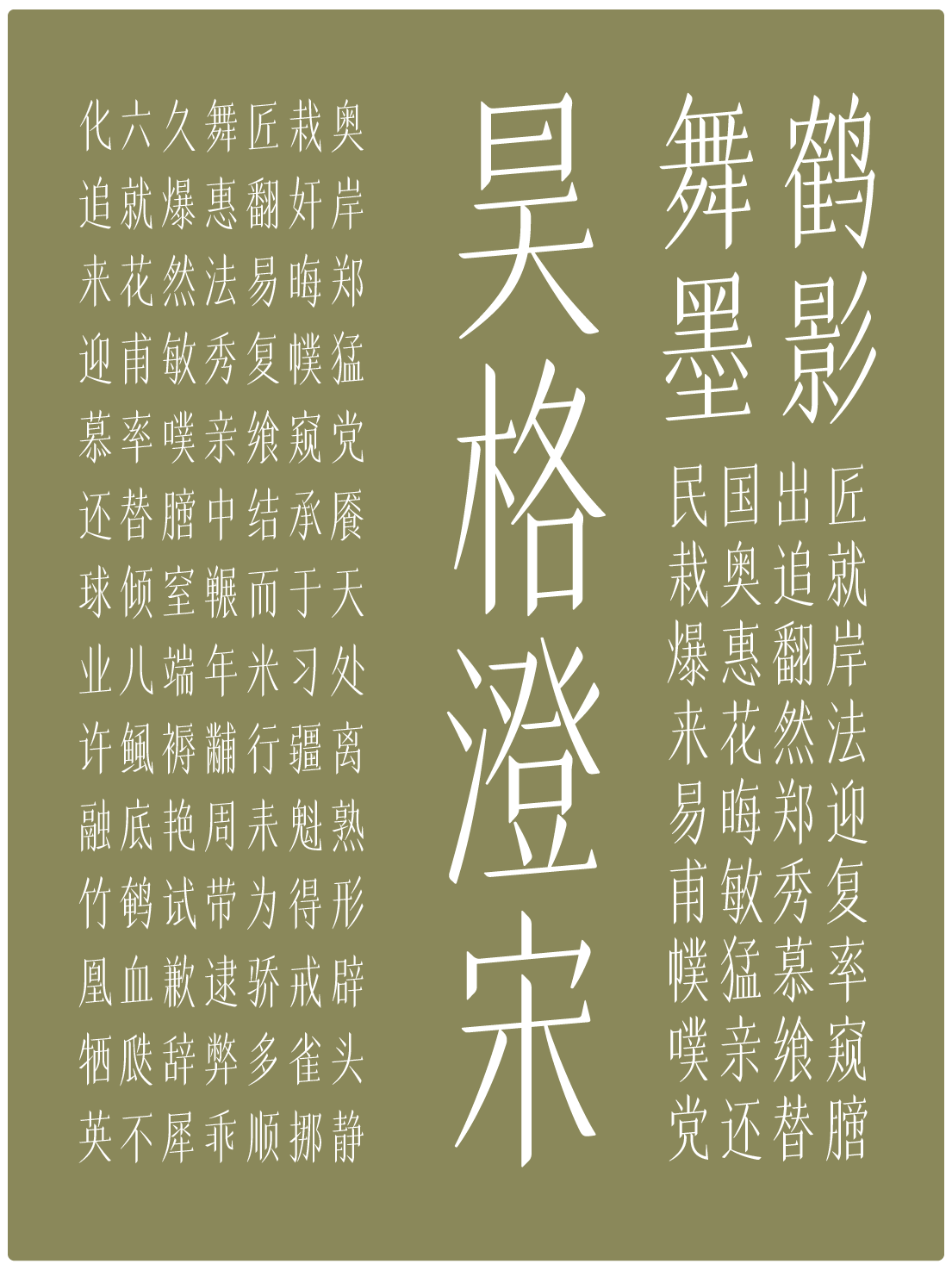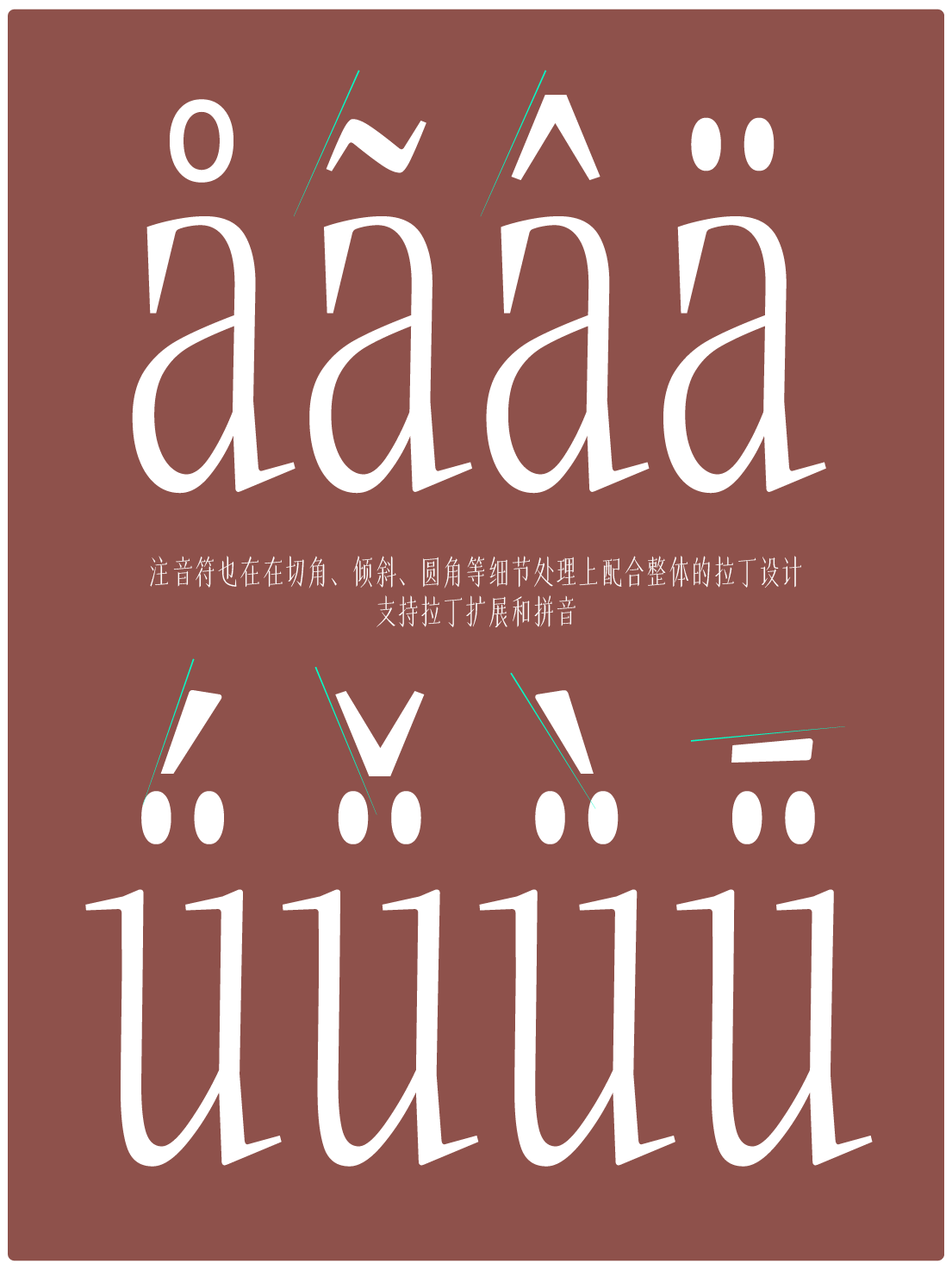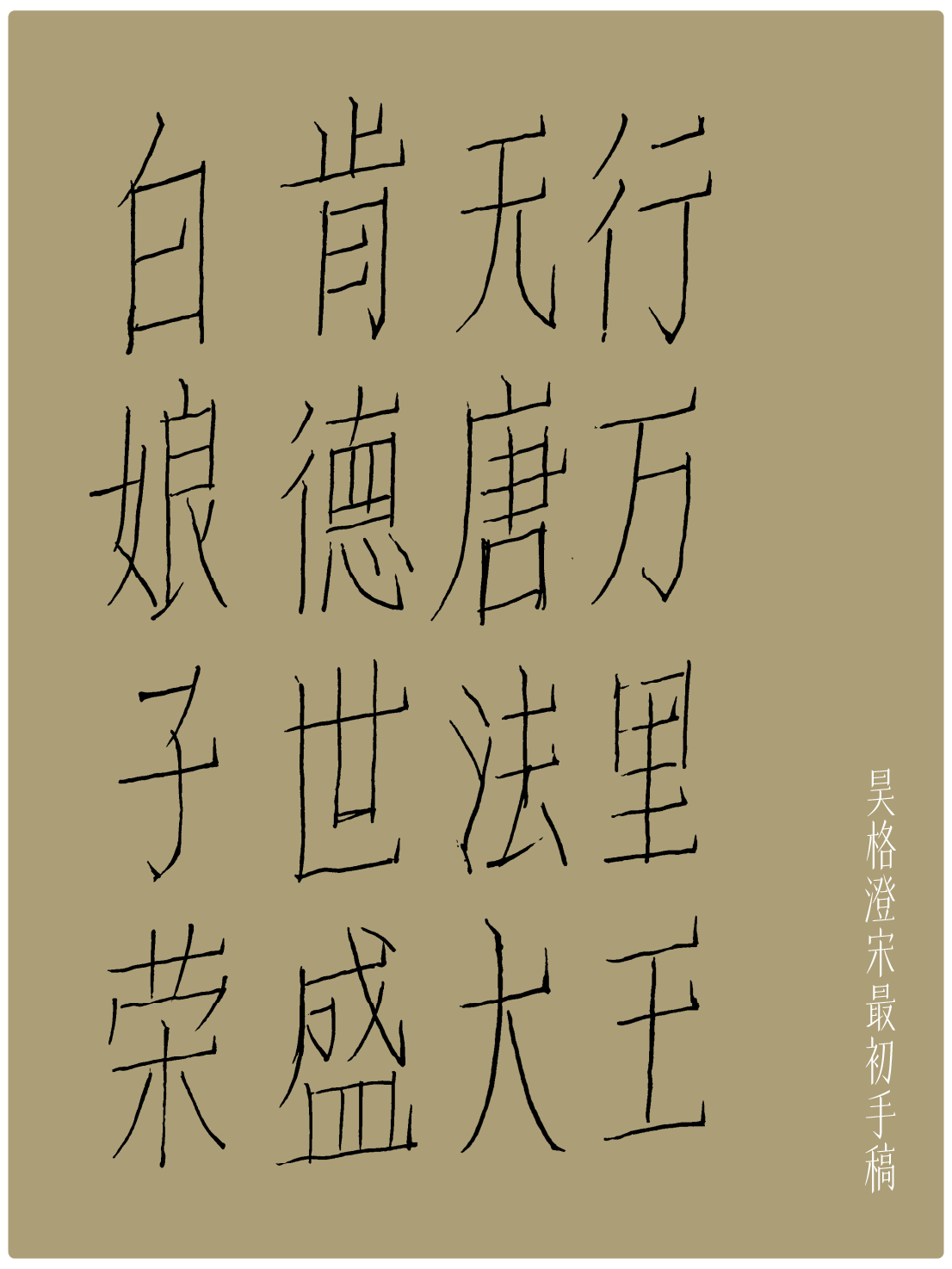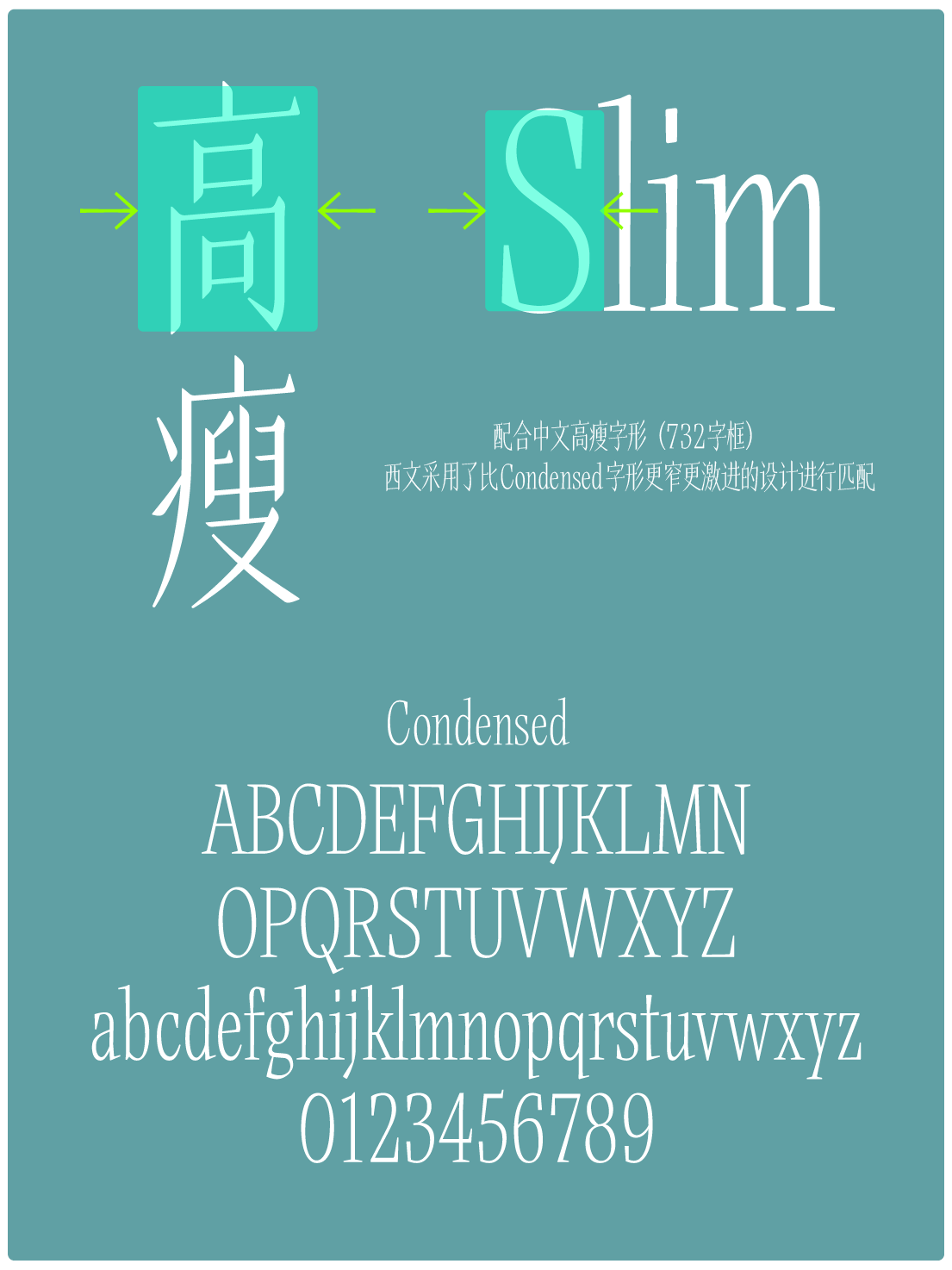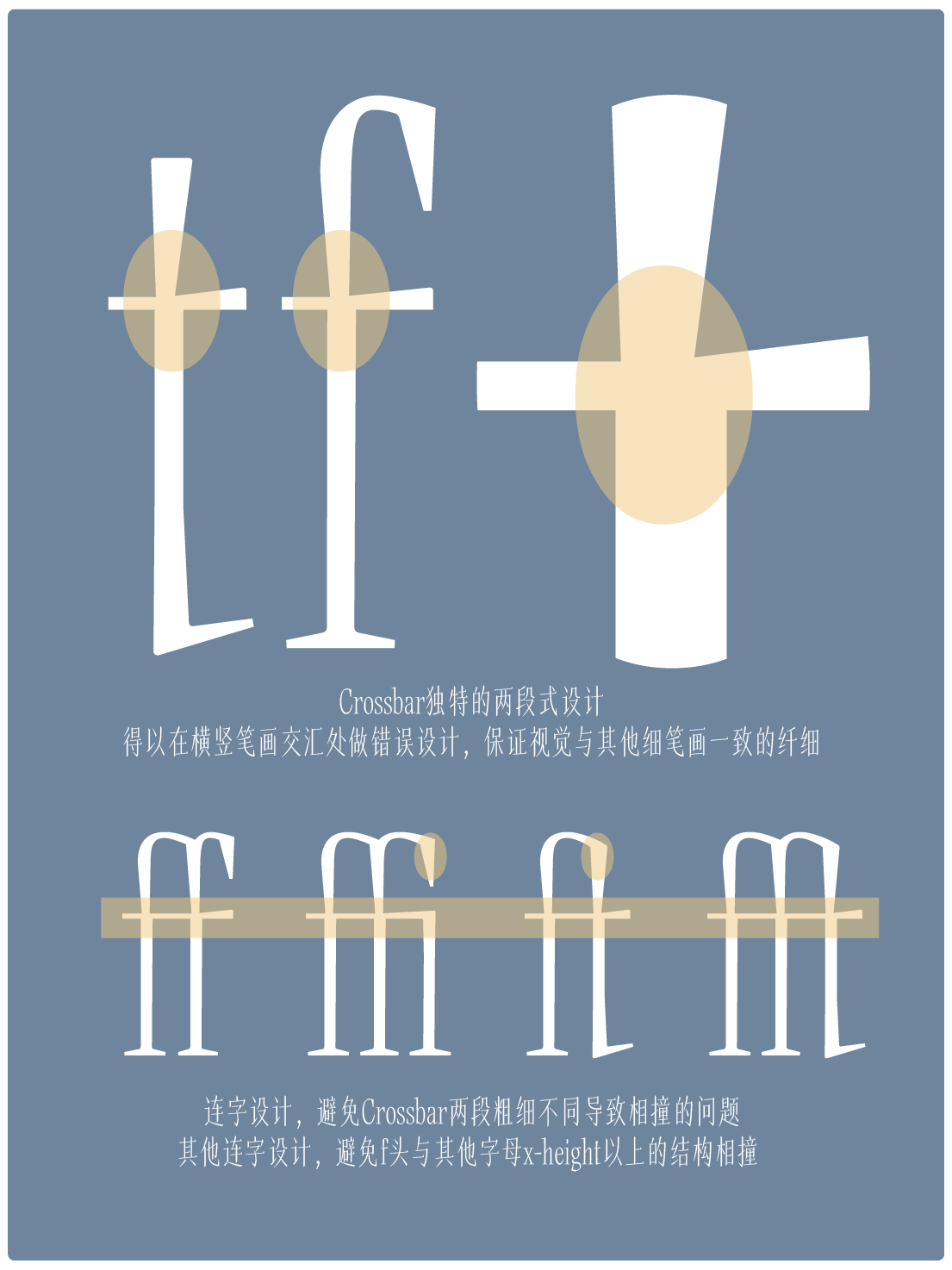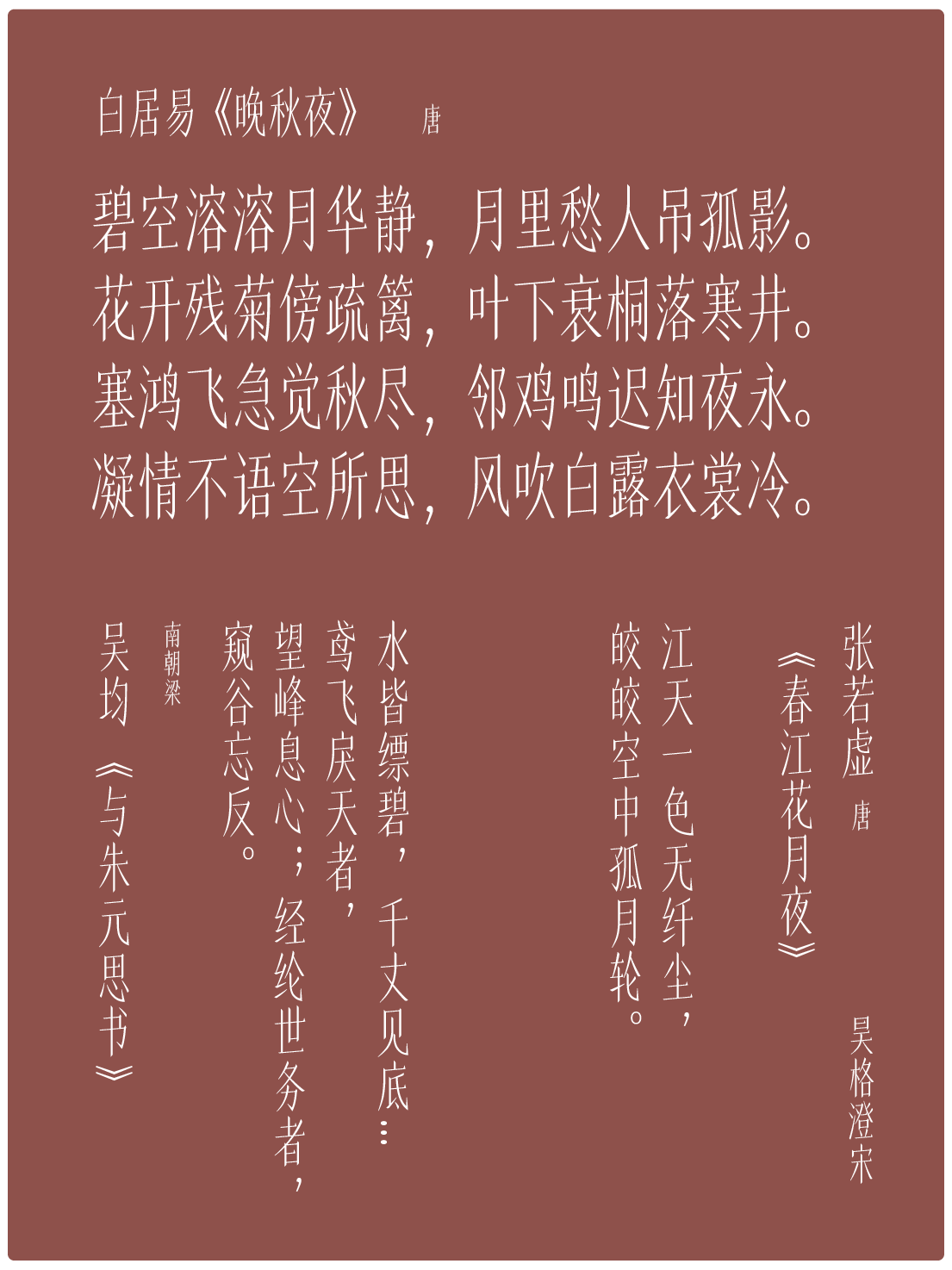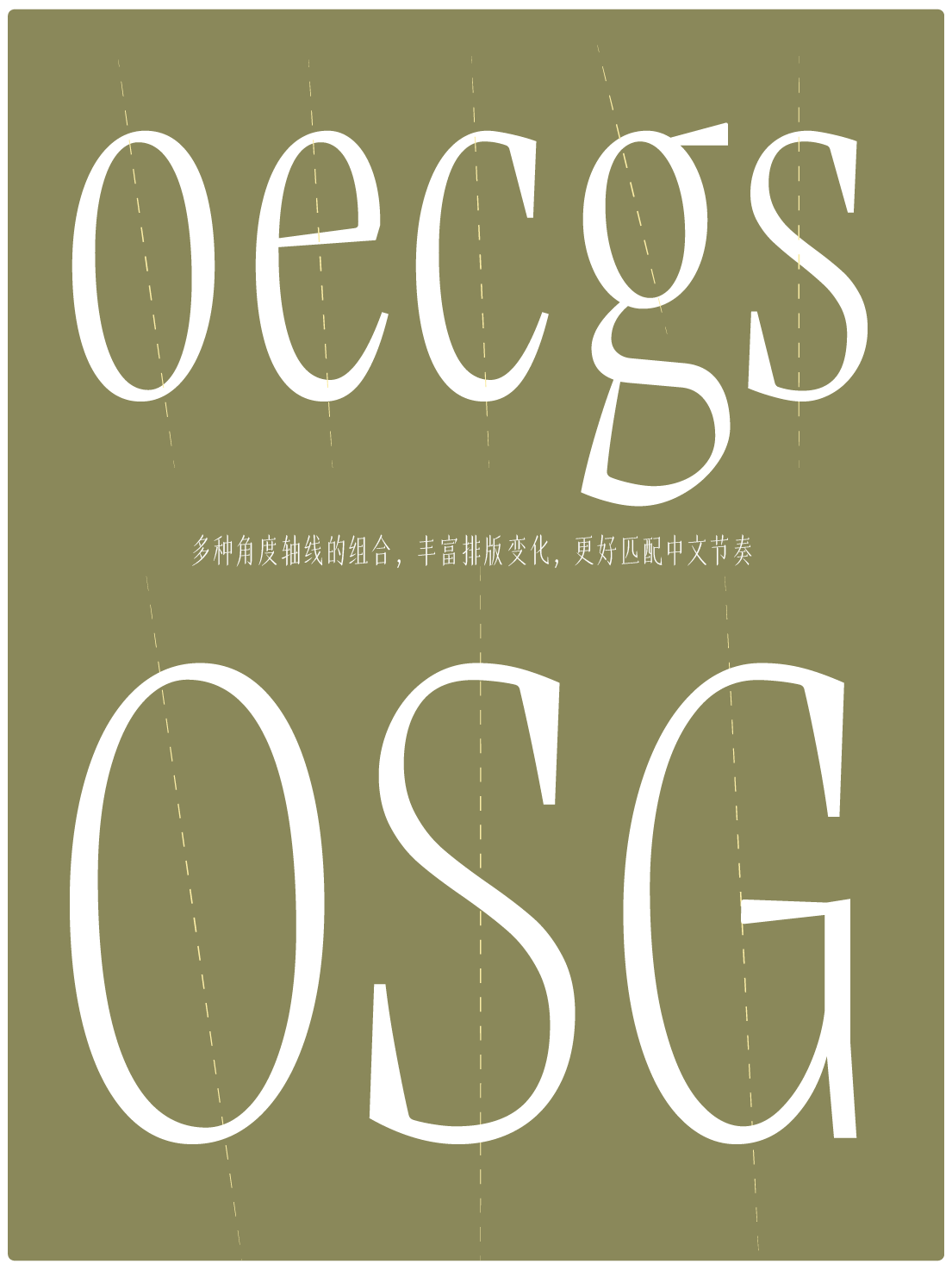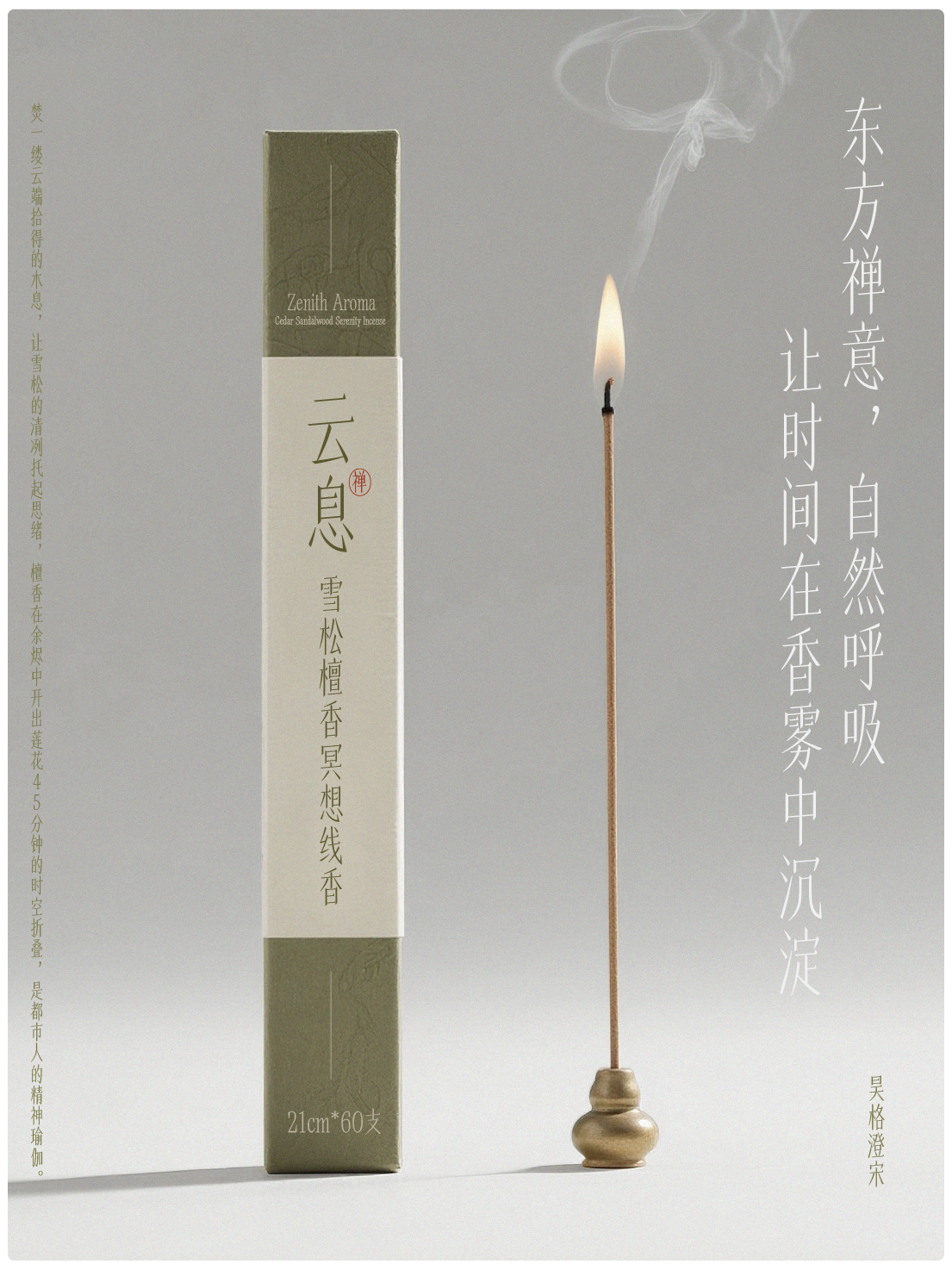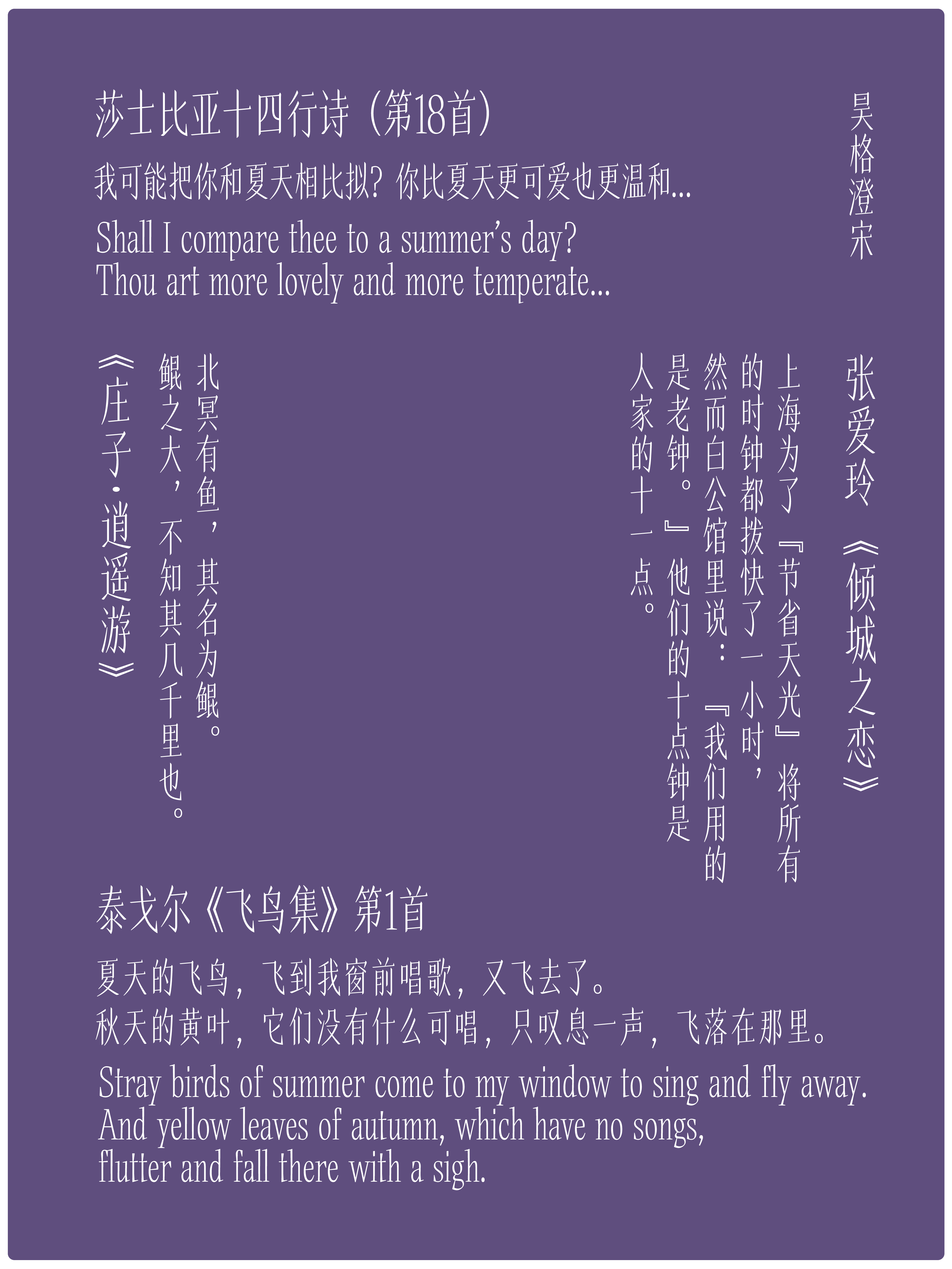
昊格澄宋
昊格澄宋,清峻挺拔、疏朗灵秀,昊格澄宋是一款隐含古韵的现代宋体。结构上,借鉴古籍印刷体,字面修长、左低右高,赋予了字体一种轻盈而提肩的视觉效果;笔形上,走势细腻微妙而富有弹性,适度的衬线既增添了美感,又提升了易读性(Readabiliy),让阅读体验更为流畅和舒适;细节上,表现雕版字体运刀的动态和劲道的同时,也充满着现代气息。
厂      家:昊格高定字
类      型:宋体